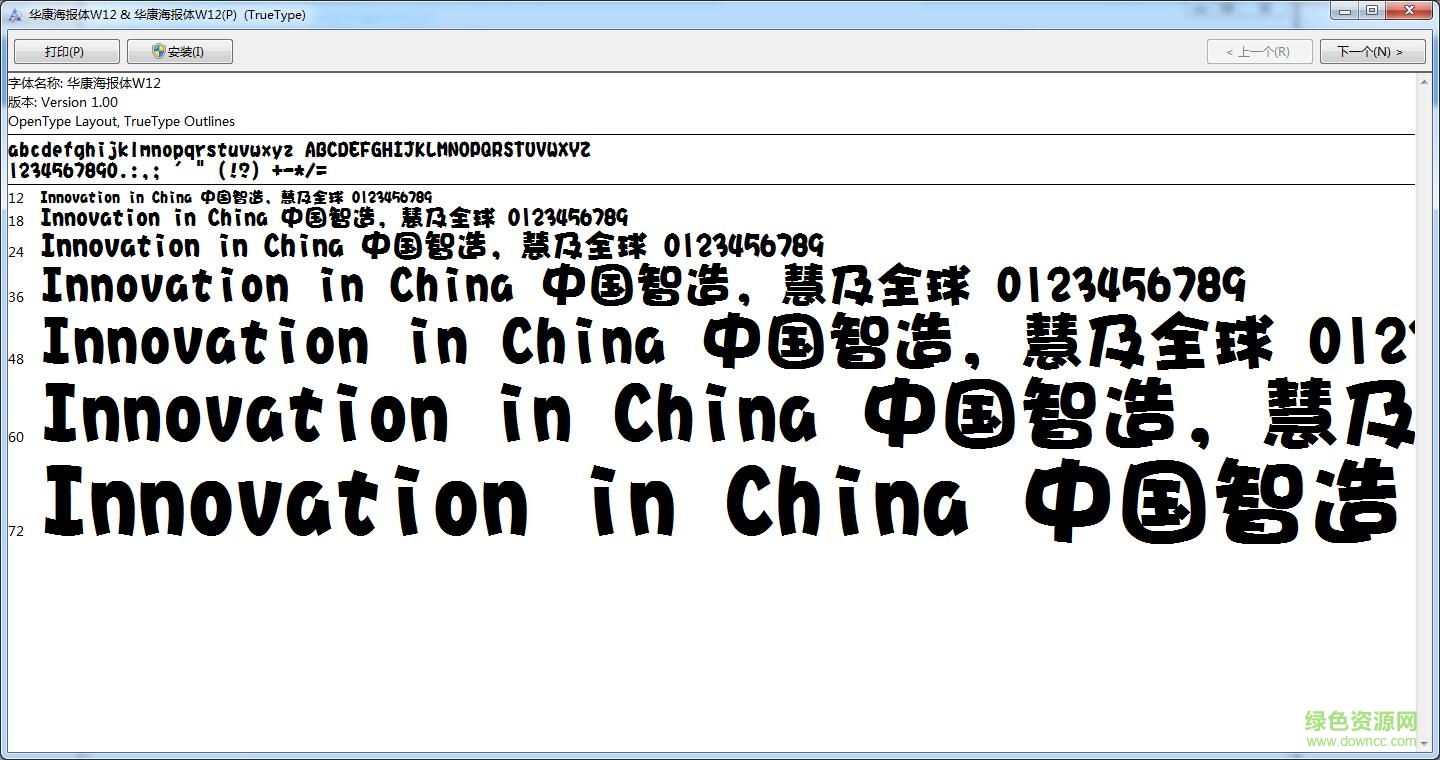
dfphaibaow12是什么字體?dfphaibaow12字體是一款ttf格式的華康海報(bào)體,字體空隙均勻,辨識(shí)度較強(qiáng),適用性好,不論是廣告海報(bào)還是雜志、書刊都可使用!
dfphaibaow12字體特點(diǎn)
它的形狀像圓性,微胖;它廣泛適用于所有領(lǐng)域,應(yīng)用于牌匾中,洛克王國(guó)游戲中的字體就是華康海報(bào)體!